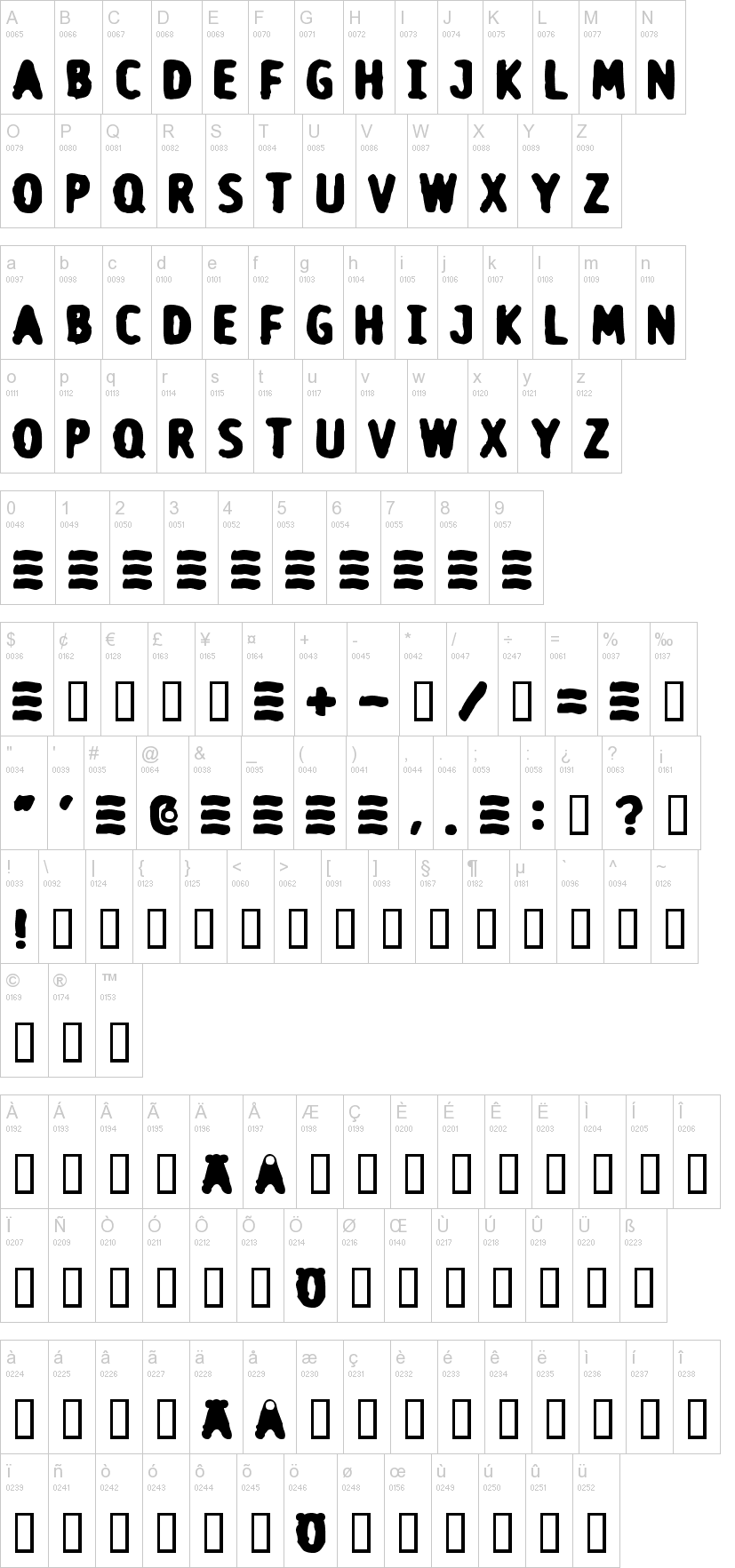
Do your thing
Do Your Thing是一款现代风格的显示字体,由Fontfabric字体工作室设计,由它的演示文本中可以看出,它是一款粗犷的字体,具有独特的外观和视觉效果,有着极具现代感的设计,适合用于标题、标识、海报等应用场景。它的字体特点是具有鲜明的视觉效果,具有较强的表现力,能够更好地表达设计者的设计理念,让视觉效果更加强烈。
Do your thing是一款非常不错的手写艺术字体,具有很好的视觉感,适合于文化类的宣传设计、商业类品牌的广告和产品包装设计以及个性化文字排版等较多场景。